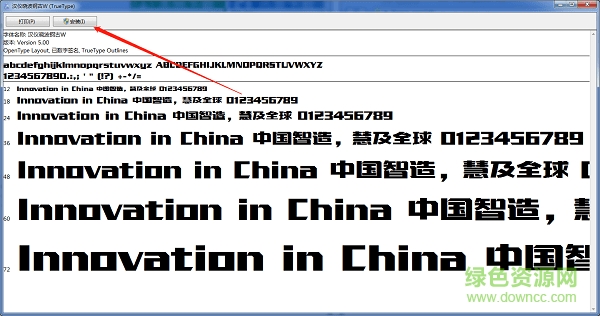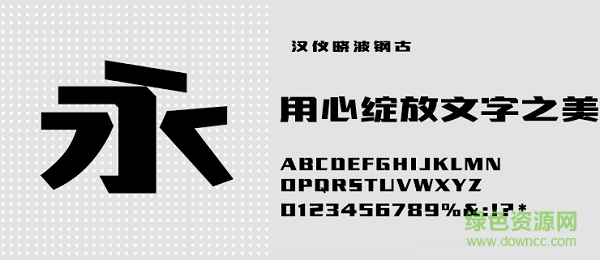
漢儀曉波鋼古體w
漢儀曉波鋼古體是一款筆鋒分明剛硬的字體,字體平整化一,有點類似于黑體字,看起來較粗,適用于整個文章標(biāo)題之處,醒目,簡單,干練,喜歡的用戶快來綠色資源網(wǎng)下載吧!
漢儀曉波鋼古w字體簡介:
漢儀曉波鋼古是一款十分大氣張揚的創(chuàng)意字體,該字體更具速度感的連筆與簡筆處理,轉(zhuǎn)折銜接處鋒利的切角,使其更具識別度與力量感,可以應(yīng)用于網(wǎng)頁設(shè)計、篆刻制模視覺設(shè)計、字帖等多個場景!
漢儀曉波鋼古字體預(yù)覽:
漢儀曉波鋼古w